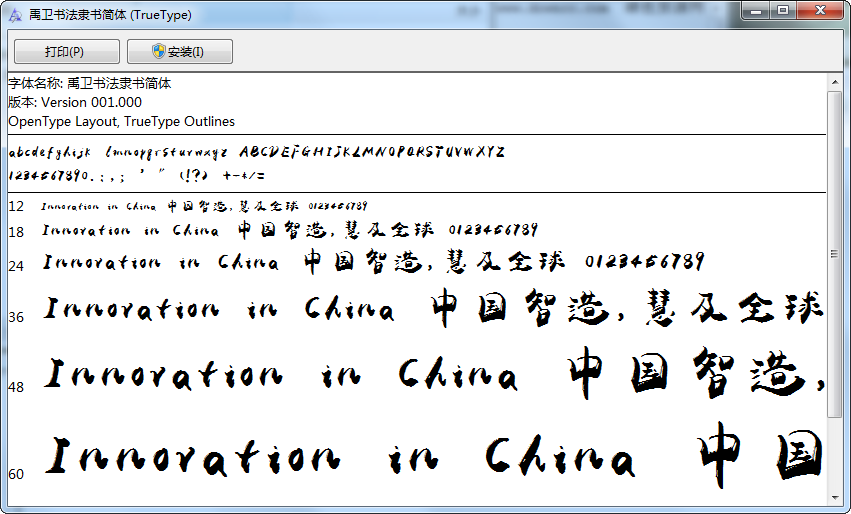
yuweilishujt
yuweilishujt字體是一款字形優(yōu)美的隸書(shū)書(shū)法字體,粗細(xì)勻稱(chēng),線條靈動(dòng),多用于古書(shū)封面設(shè)計(jì)、藝術(shù)設(shè)計(jì)、影視海報(bào)等方面,有需要者歡迎下載使用!
書(shū)法字體類(lèi)型介紹
書(shū)法字體,傳統(tǒng)講共有行書(shū)字體、草書(shū)字體、隸書(shū)字體篆書(shū)字體楷書(shū)字體五種,也就是五個(gè)大類(lèi)。在每一大類(lèi)中又細(xì)分若干小的門(mén)類(lèi),如篆書(shū)又分大篆、小篆,楷書(shū)又有魏碑、唐楷之分,草書(shū)又有章草、今草、狂草之分。
yuweilishujt
隸書(shū)隸變過(guò)程介紹
隸變?cè)谥袊?guó)書(shū)法史上是一次重大的書(shū)法文化事件。發(fā)生隸變的內(nèi)在動(dòng)因是為了適應(yīng)當(dāng)時(shí)社會(huì)發(fā)展對(duì)文字應(yīng)用的要求?!半`變主要表現(xiàn)在兩個(gè)方面:一是字形結(jié)構(gòu)的變化,既是對(duì)正體篆書(shū)字形結(jié)構(gòu)的改造,這種改造的主要方向是簡(jiǎn)化;二是書(shū)寫(xiě)方式的變化,既是改變?cè)姓w篆書(shū)的書(shū)寫(xiě)方式,這種改變的主要目的是簡(jiǎn)捷流便”。字形結(jié)構(gòu)的簡(jiǎn)化和書(shū)寫(xiě)方式的簡(jiǎn)捷流便構(gòu)成了隸變過(guò)程的核心內(nèi)容。